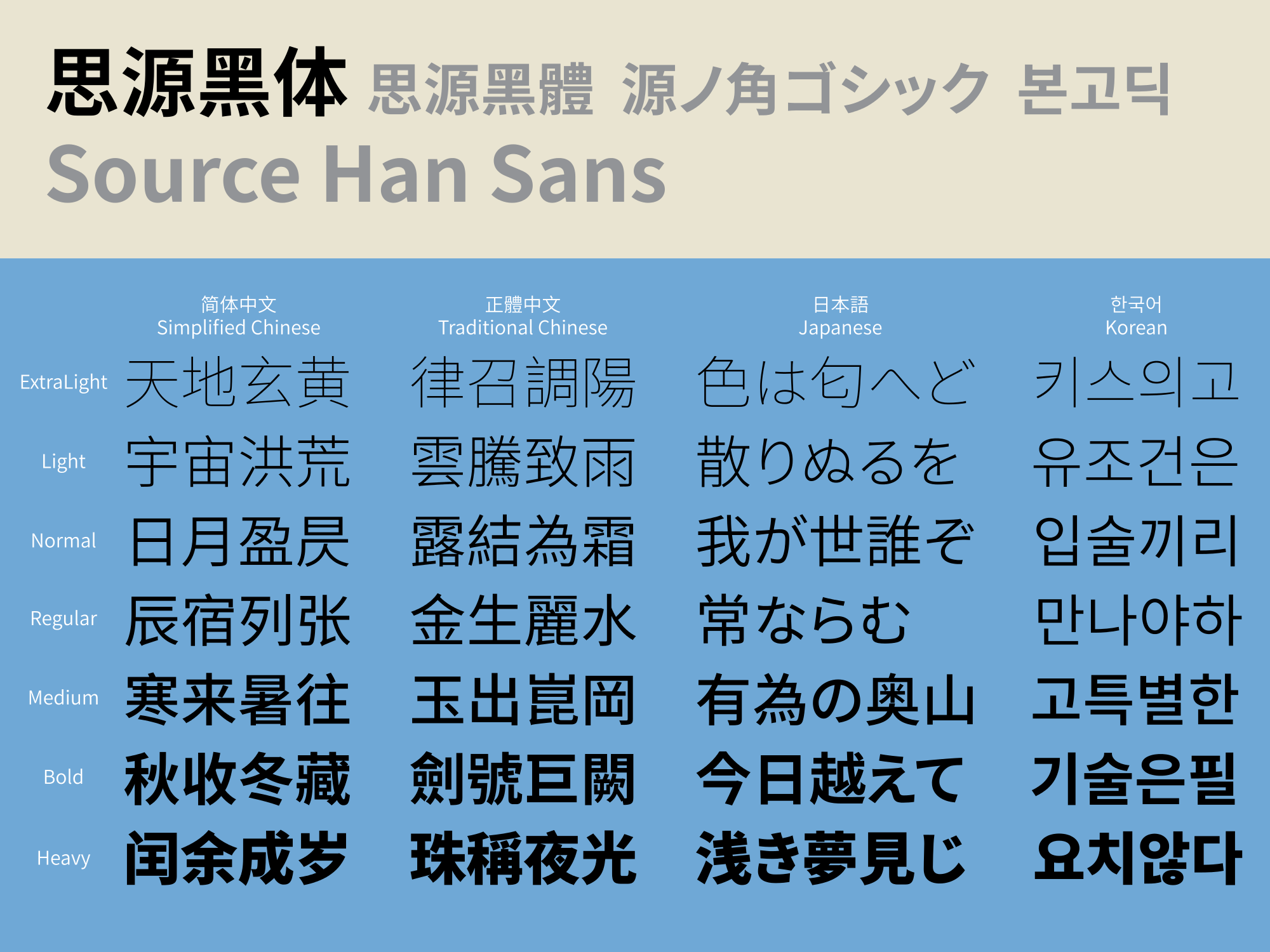
思源黑体(英语:Source Han Sans)是Adobe与Google所领导开发的开源字体家族,1.001及更早版本以Apache 2.0许可证授权,而1.002及更新版本则使用SIL开源字体授权,属于无衬线黑体。思源黑体于2014年7月16日首次发布,支持繁体中文、简体中文、日文及韩文,并且各有7种字体粗细。公开之时为当时涵盖字元数量最多的字体,44,666个字元分属于65,535个字形中,此为OpenType字体技术的极限。